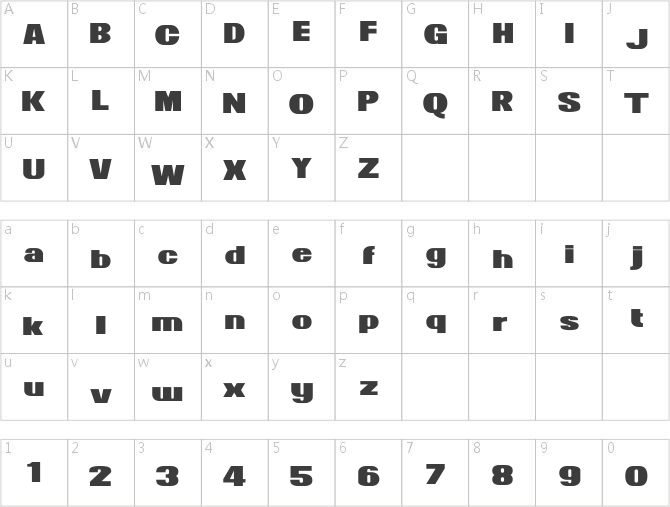
News of the World wide 详情页
字体名称: News of
News of the World wide
News of the World wide字体字库是一款让人赏心悦目、百看不厌的英文字体,适合各类广告和产品包装设计应用,字体大小0.09MB,格式为ttf字体,上传用户是我,Dirac,作者/版权方为未知